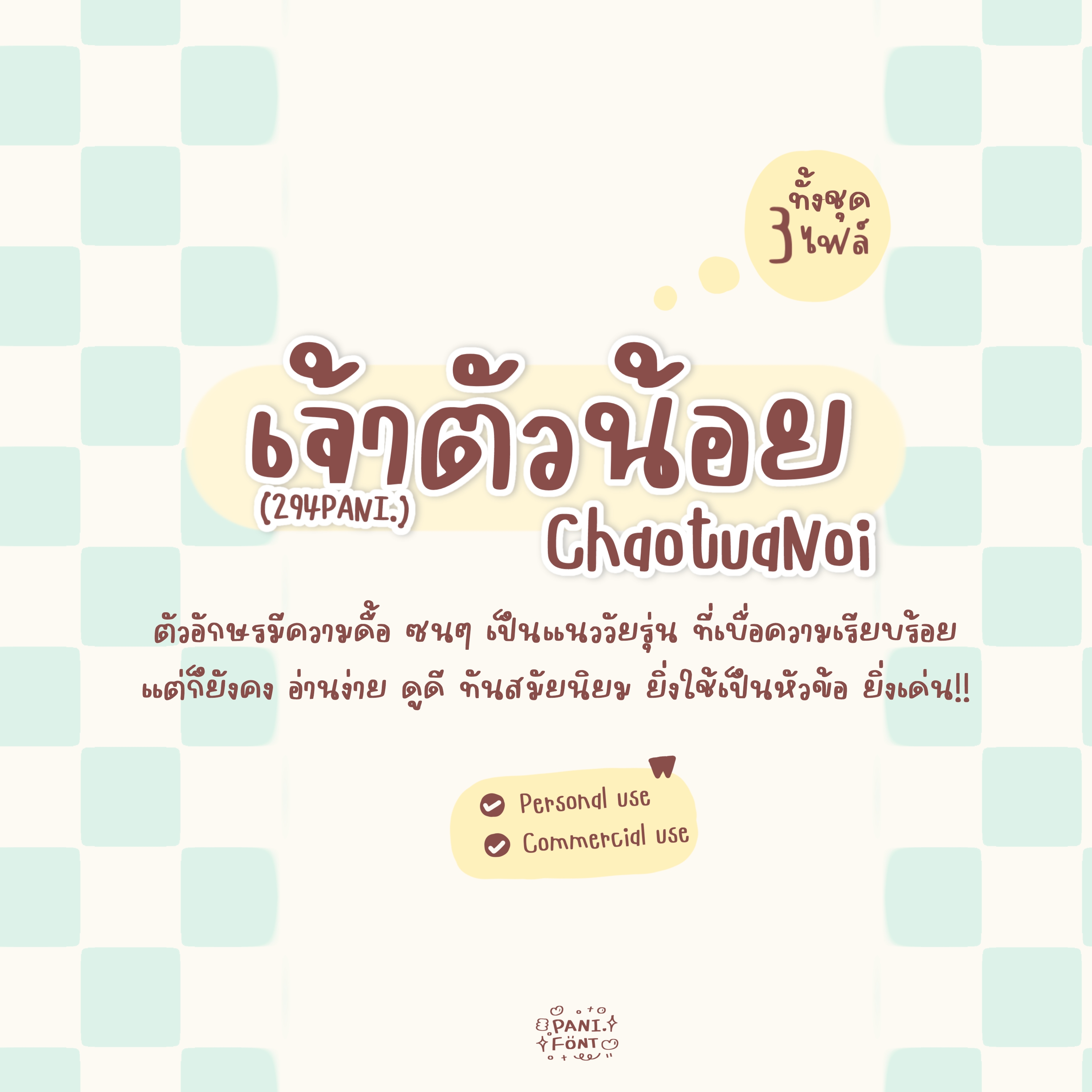
ฟอนต์เจ้าตัวน้อย
ฟอนต์เจ้าตัวน้อย ตัวอักษรมีความดื้อ ซนๆ
เป็นแนววัยรุ่น ที่เบื่อความเรียบร้อย แต่ก็ยังคง อ่านง่าย
ดูดี ทันสมัยนิยม *ยิ่งใช้เป็นหัวข้อ ยิ่งเด่น!!
จะตั้งเครื่อง ก็น่ารัก/อ่านรายละเอียดก็สบายตา เก๋ๆ/แต่งภาพ ก็เด่นสะดุดตา ครบเครื่อง ไม่ซ้ำใคร!